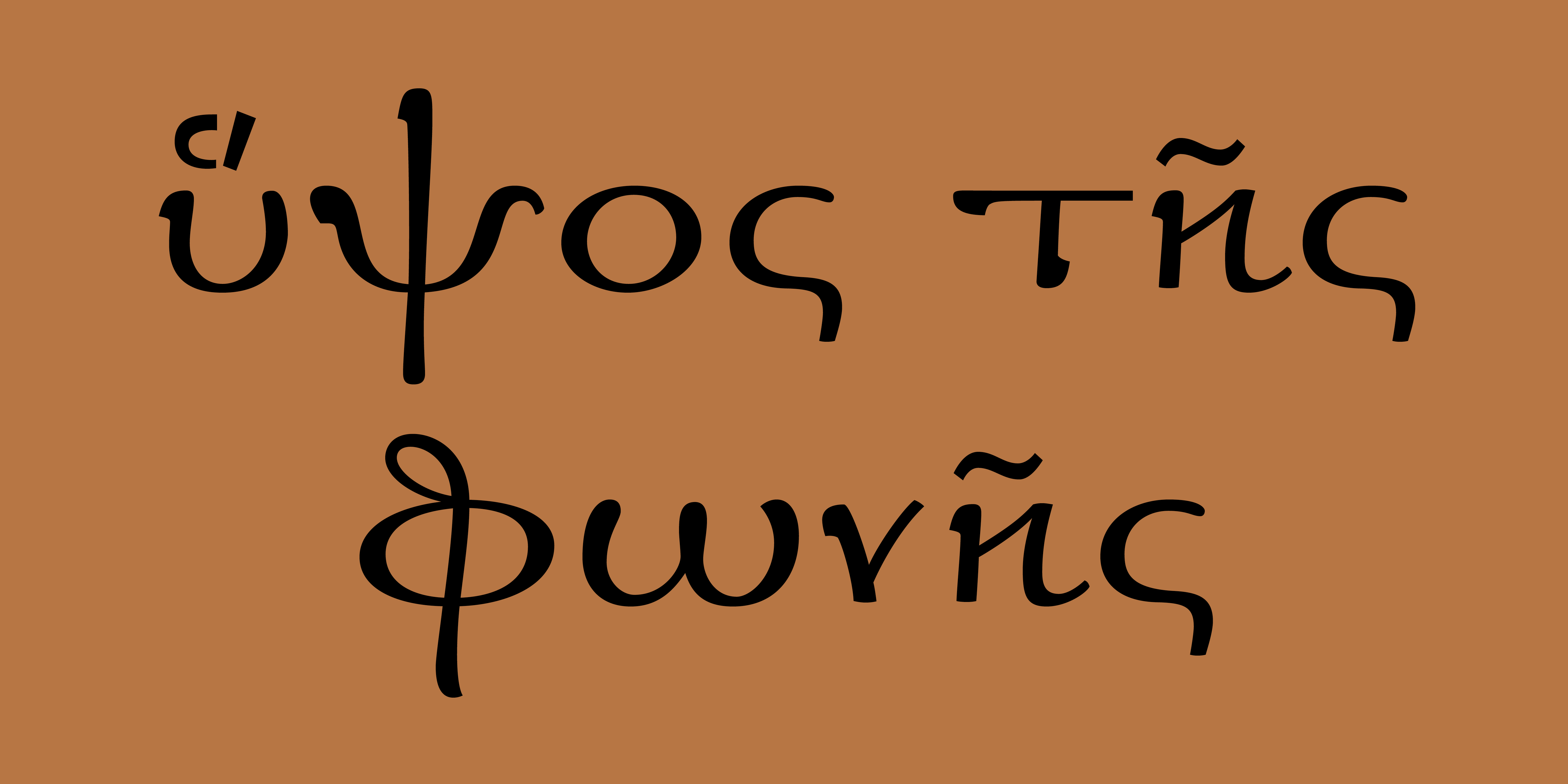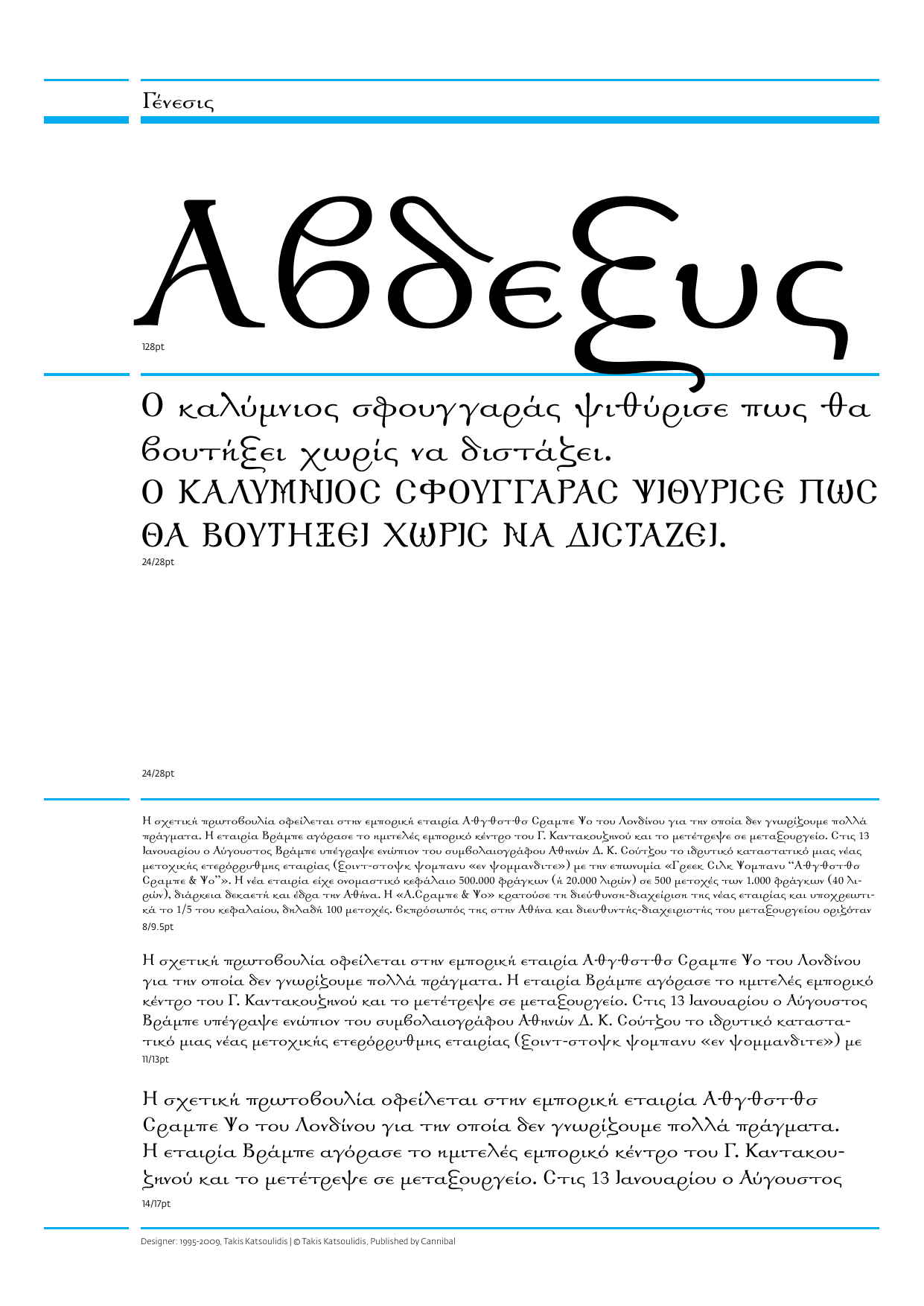
Genesis Πολυτονικά
Το 1995, με αφορμή το λεύκωμα «ΓENEΣIΣ» των εκδόσεων τέχνης του N. Γρηγοράκη, σχεδιάστηκε η γραμματοσειρά «Γένεσις», στηριγμένη στη Βυζαντινή καλλιγραφία. Η νέα έκδοση που κυκλοφορεί από το 2010 είναι επανασχεδιασμένη ενώ έχει νέα σύμβολα και εναλλακτικούς χαρακτήρες ώστε να ταιριάζουν αρμονικά μεταξύ τους οι δύο παραλλαγές, Regular και Bold. Η «Γένεσις» υποστηρίζει πλήρως Ελληνικούς μονοτονικούς, πολυτονικούς και αρχαϊκούς χαρακτήρες.